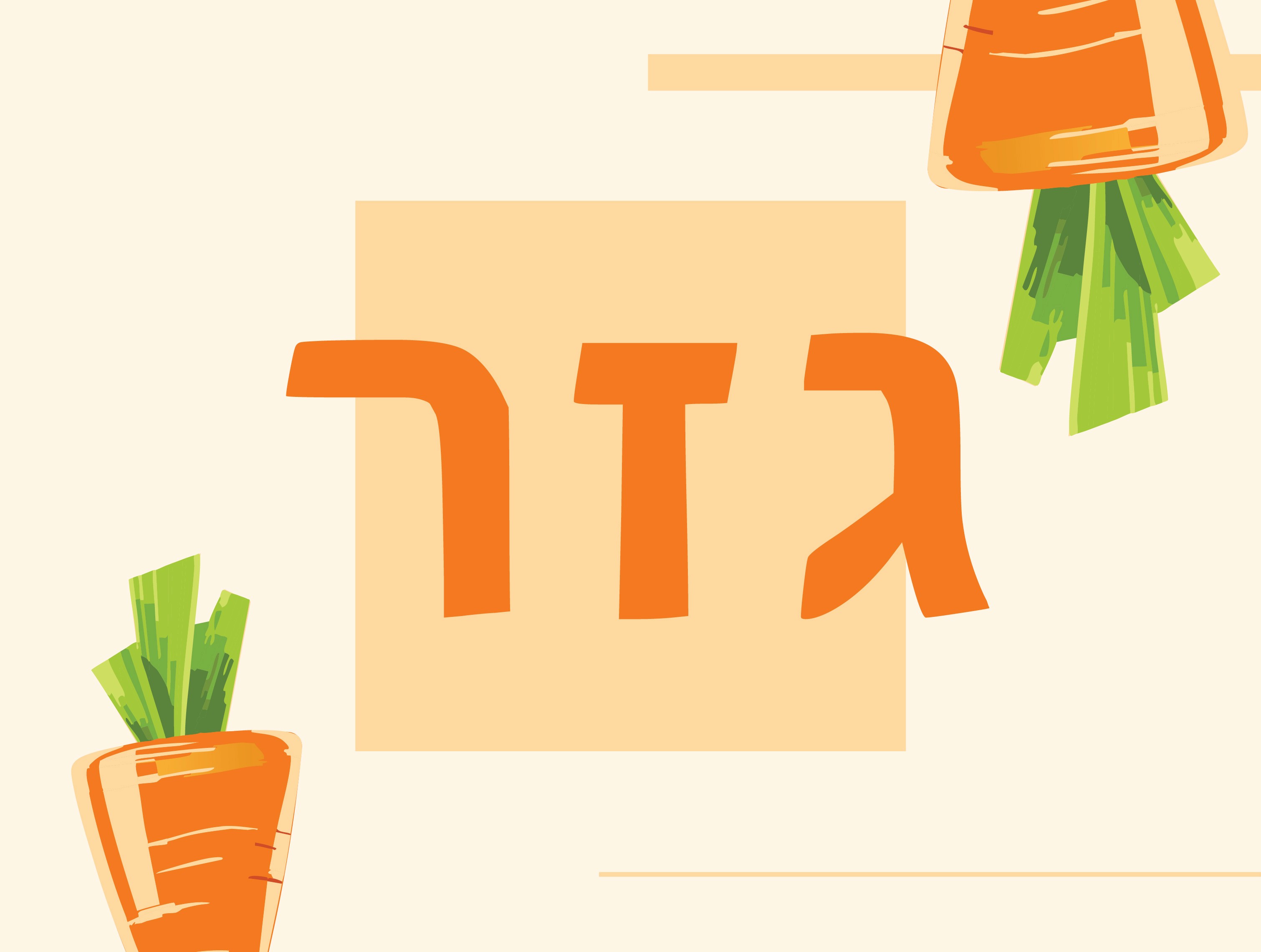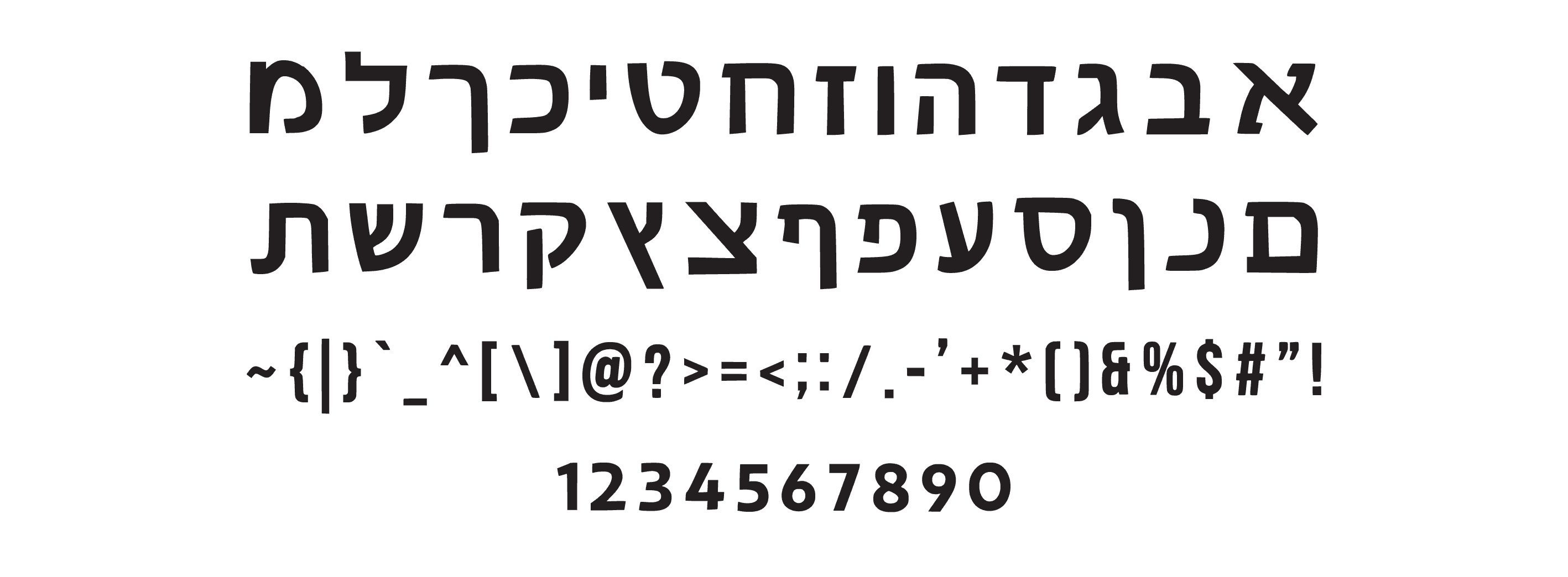
גזר פונט
Thick, soft and pleasant Hebrew font, perfect for natural branding, food designs and rustic posters.
גזר — פונט עם טעם של בית
גזר הוא בדיוק השילוב המושלם בין פשטות נעימה לאופי כובש.
הוא עבה וקריא, אבל גם שומר על קווים רכים ועגולים שנותנים לו אופי חמים ומזמין.
יש בו משהו שמזכיר אותיות גזורות ידנית או כתב יד מוקפד, כזה שמתאים לעיצובים עם טאץ' אישי אבל לא מתאמץ.
הוא מרגיש בבית בעיצובים טבעיים, חקלאיים, קולינריים ואפילו במיתוגים שמחפשים לשדר תחושת קהילה וחמ暖ות.
איפה הוא מרגיש בבית?
🥕 מיתוגים של אוכל טבעי, בריא או אורגני
🥕 פוסטרים ואריזות בסגנון כפרי
🥕 חנויות בוטיק, בתי קפה ומסעדות
🥕 עיצובים משפחתיים ואירועי קהילה
למי הוא מתאים?
למעצבים, בעלי עסקים ואנשי מיתוג שמחפשים פונט נגיש, רך ומזמין עם מראה טבעי וכפרי.